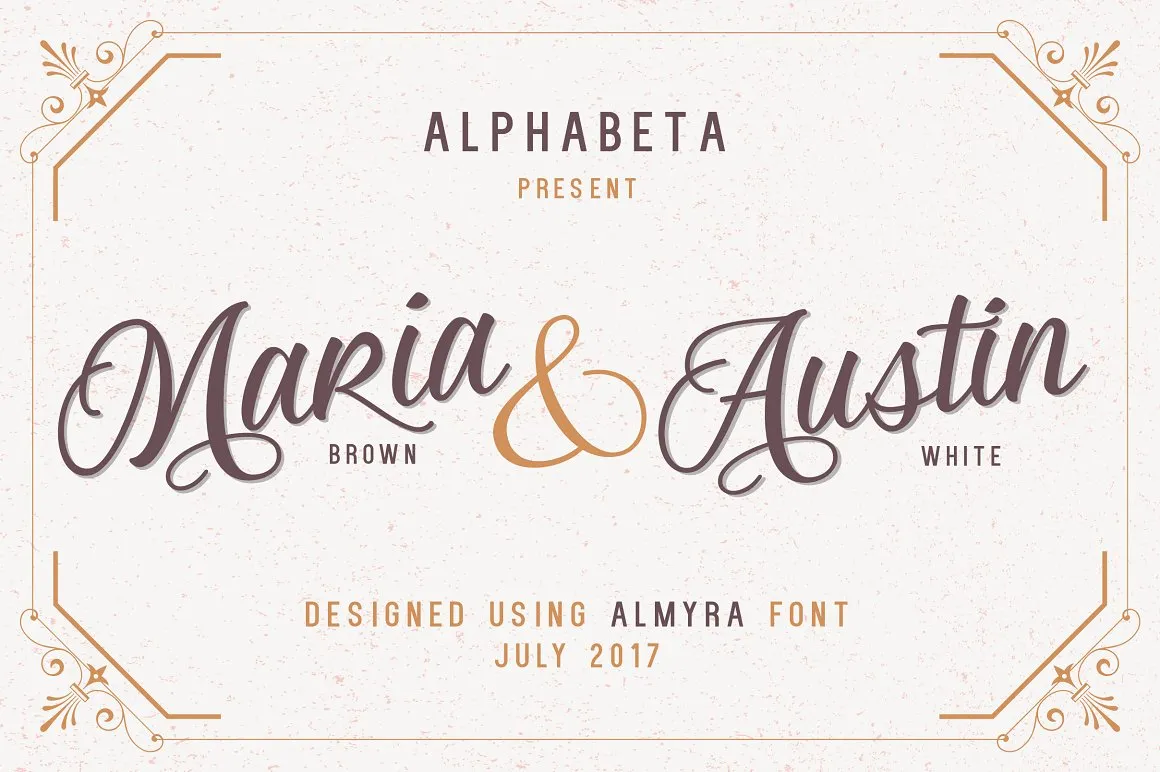
Almyra Script Font é uma elegante fonte que surgiu inspirada no charme e na personalidade única de uma pessoa especial. Criada pelo designer 178-MC, essa fonte premium está disponível gratuitamente para download nesta plataforma. Inspirada em suas risadas, sorrisos e paixão, a fonte Almyra é um convite ao luxo e à sofisticação, com seu belo conjunto de letras maiúsculas e minúsculas. O design inclui uma variedade de estilos, alternativas para criar textos mais variados e suporte multilíngue. Seja você designer gráfico ou webmaster, Almyra é perfeita para dar um toque único a qualquer projeto – sua complexidade e elegância farão o seu trabalho brilhar ainda mais.